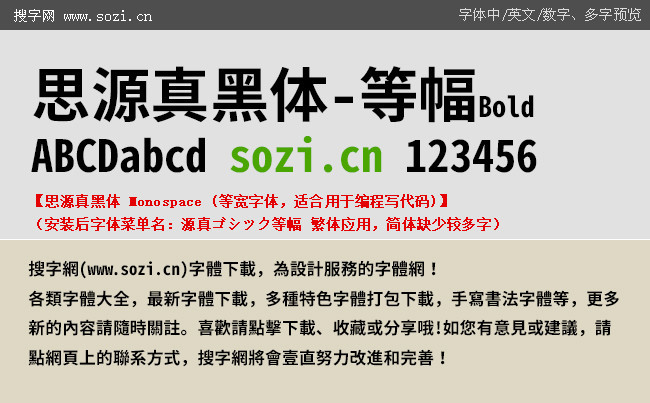
思源真黑體-等幅Bold
搜字網(wǎng)給大家提供一款思源真黑體-等幅Bold中文字體下載,思源真黑體字體是源于Google的開源字體思源黑體,保留了思源黑體原版的優(yōu)雅以及高可讀性的特色,并在思源黑體的基礎(chǔ)上做出了變化,使得整套字體看起來更加銳利清晰。等寬字體 GenJyuuGothic - Monospace適合用于編程寫代碼。